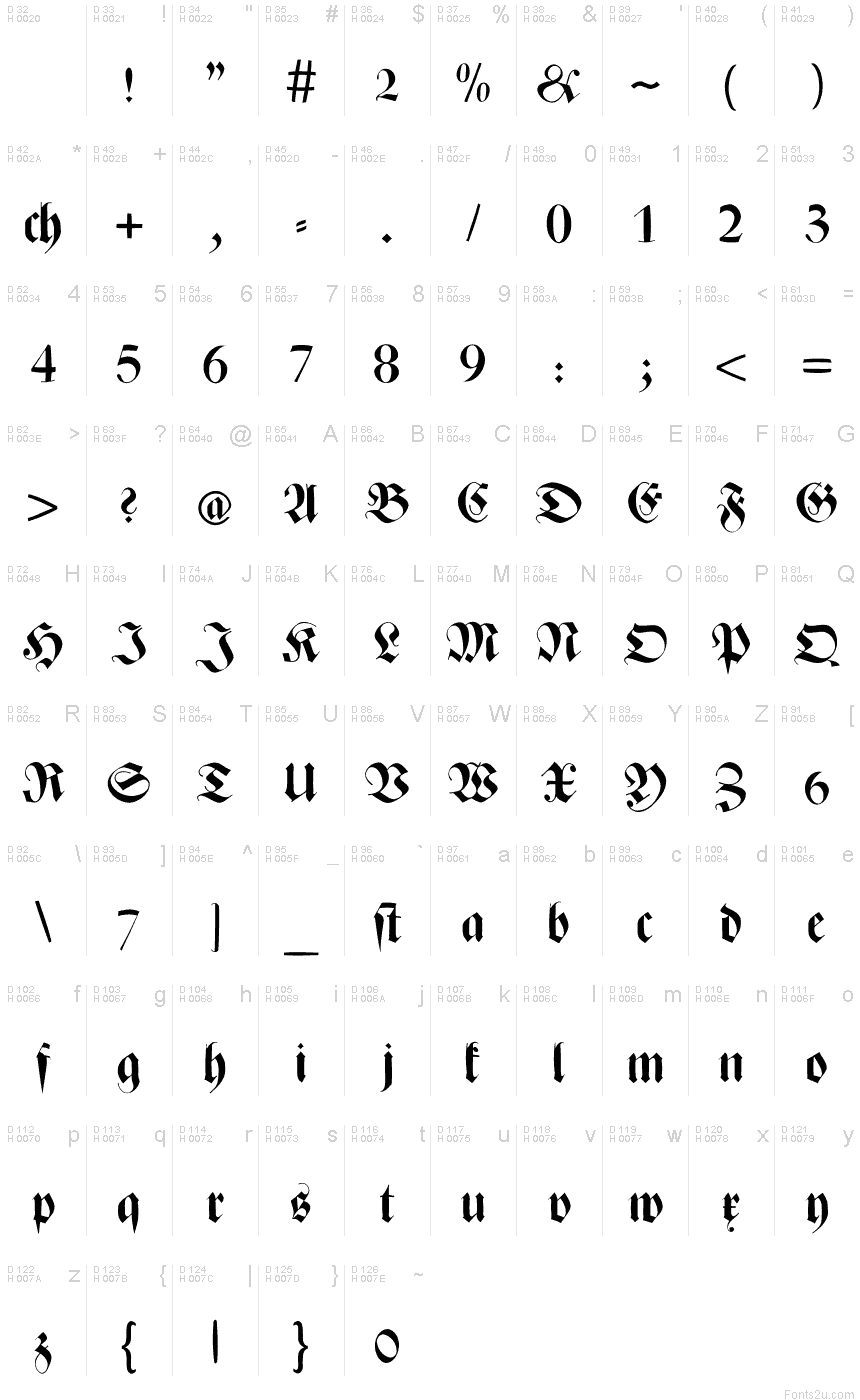
Zen Frax autorstwa Manfreda Kleina to darmowy gotycki krój pisma o wyrazistym, kaligraficznym charakterze. Litery oparte są na łamanych krzywych, ostrych łączeniach i charakterystycznych dla blackletteru zawijasach, co nadaje całości starodawny, ceremonialny, a nie surowy klimat.
Sprawdza się na plakatach, okładkach książek, w identyfikacji wizualnej fantasy, grafikach eventowych czy oprawach muzycznych, gdzie potrzebny jest klimat dawnej epoki, ale bez zbędnego przepychu. Dzięki połączeniu zwartych, ciemnych kresek z długimi, wijącymi się akcentami, ZenFrax świetnie prezentuje się w krótkich nagłówkach, tytułach i inicjałach typu monogram, gdzie te ozdobniki mają przestrzeń, by wybrzmieć.